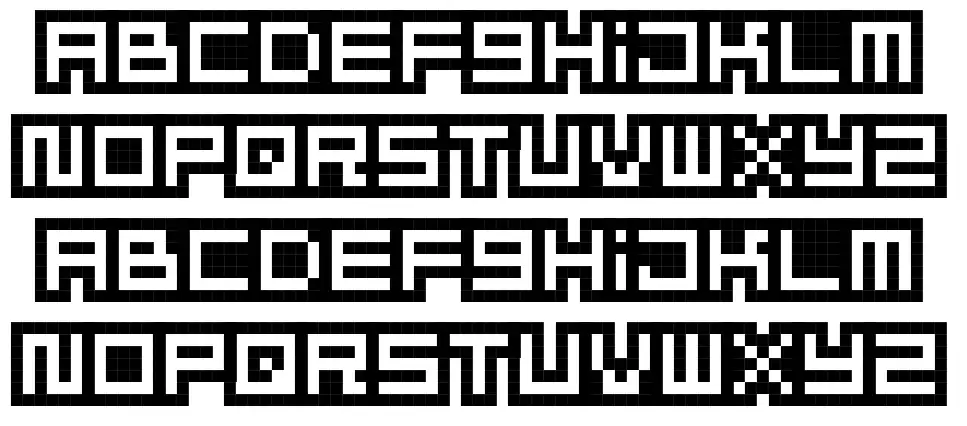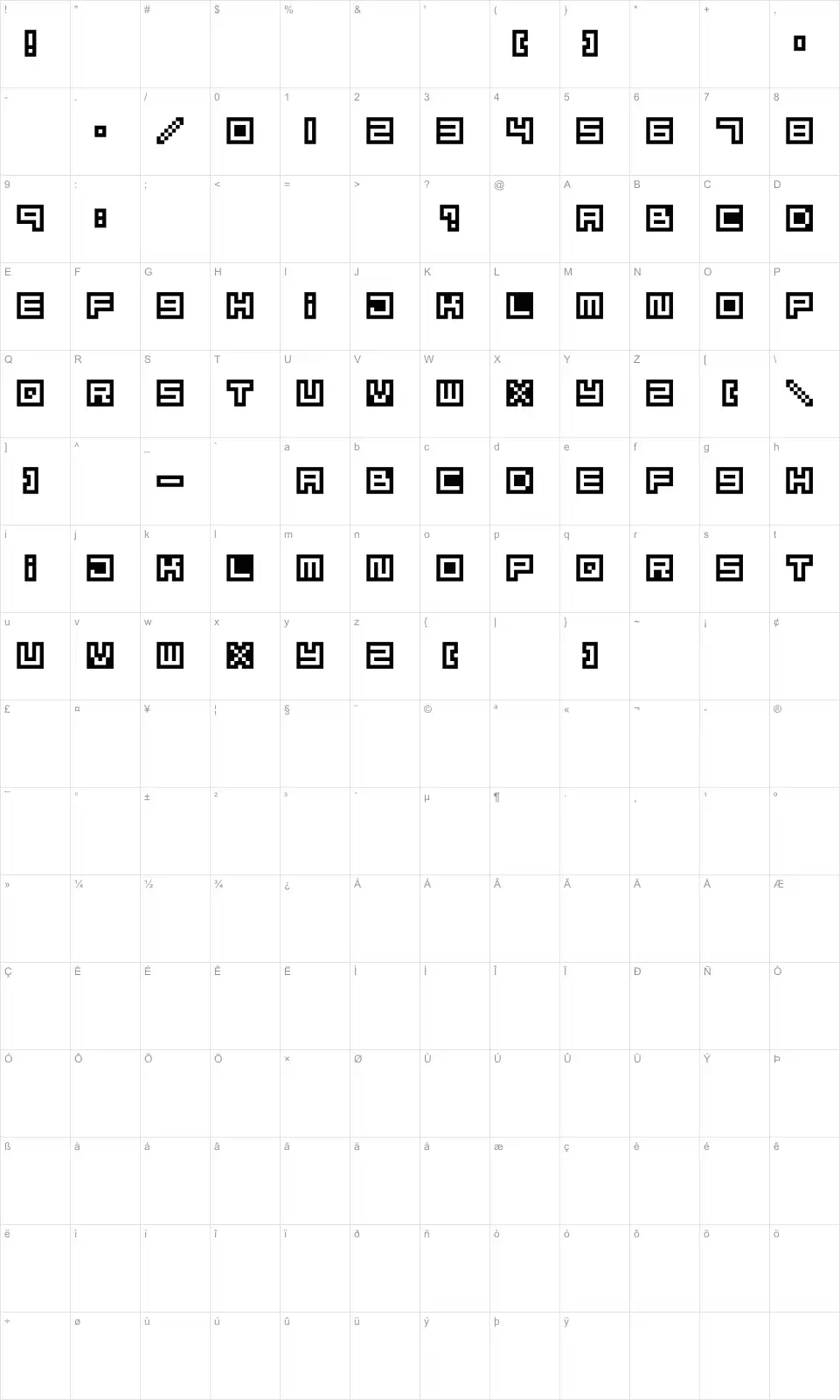
Mizu Font Alphabet – Download Grátis
Descubra a Mizu Font Alphabet, uma elegante fonte de tipo para a categoria Techno. Desenvolvida pelo designer sk89q, esta fonte apresenta um visual pixelizado que combina perfeitamente com os estilos modernos e futuristas que dominam a tecnologia atual. Se você está buscando uma fonte única para seus projetos tecnológicos, a Mizu Font Alphabet é uma ótima escolha. Ela está disponível em formato TTF para download gratuito para uso pessoal, com downloads já contabilizando centenas. Com seu tamanho de 6 KB, a Mizu Font Alphabet se destaca como uma opção leve e conveniente para projetos online. Para uma visualização prévia de seus textos antes de implementá-la em um projeto, você pode gerar um preview personalizado online. Para mais informações ou para acessar o design de sk89q, visite o site http://www.therisenrealm.com.
Designer: sk89q